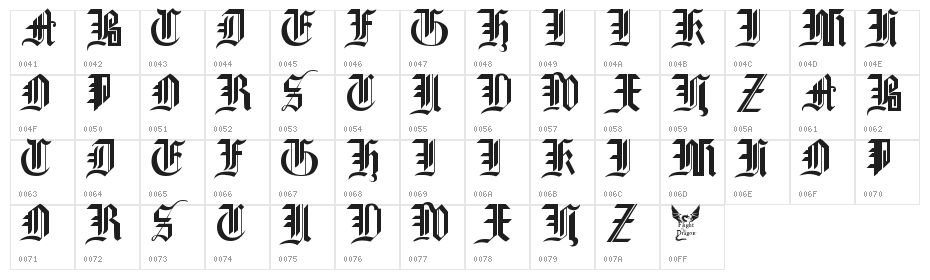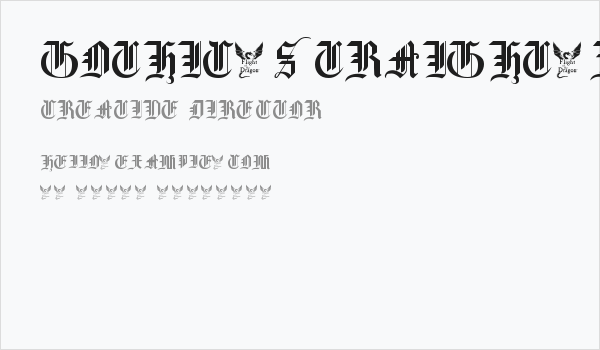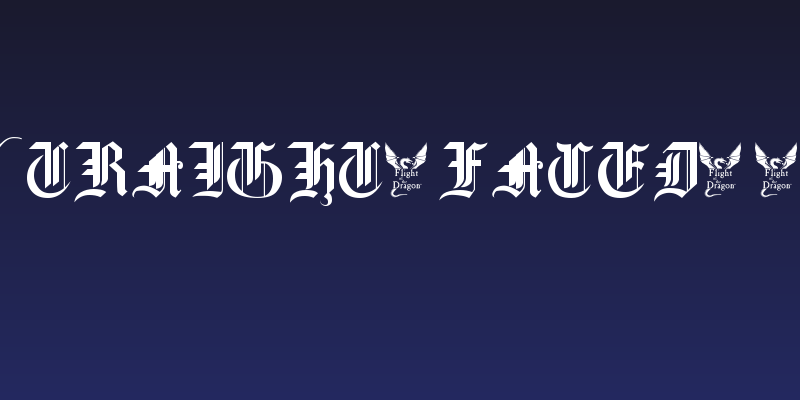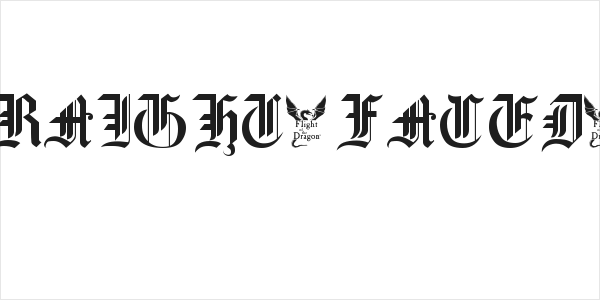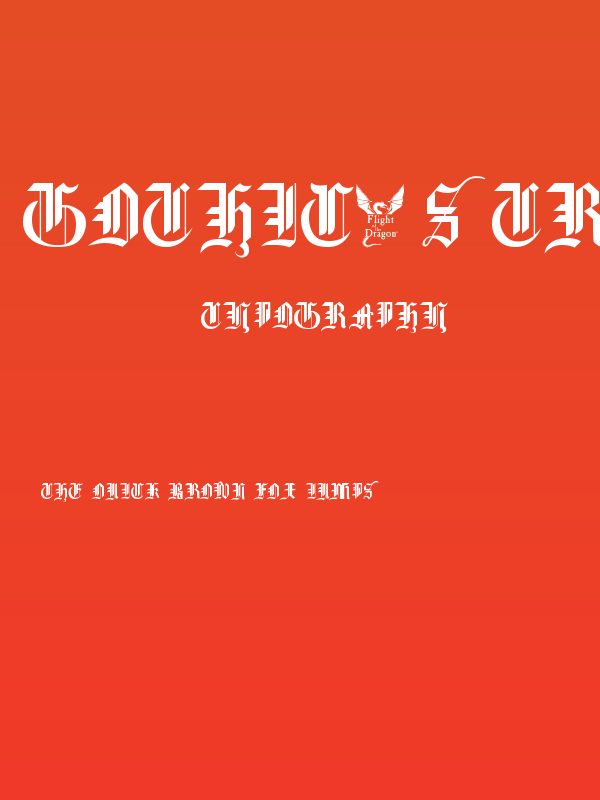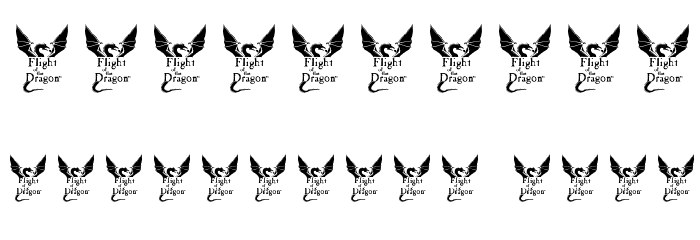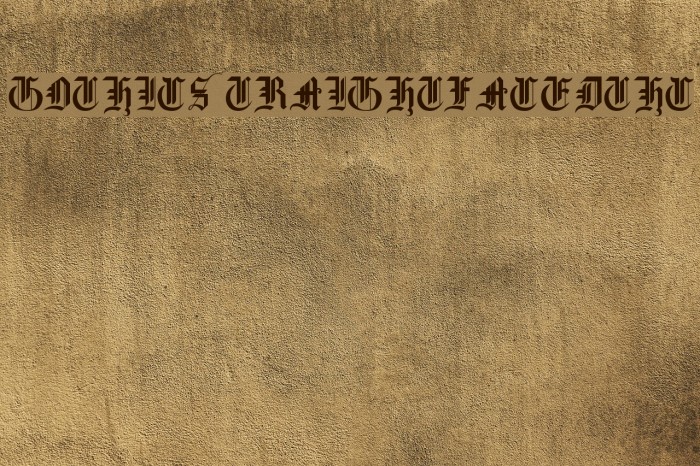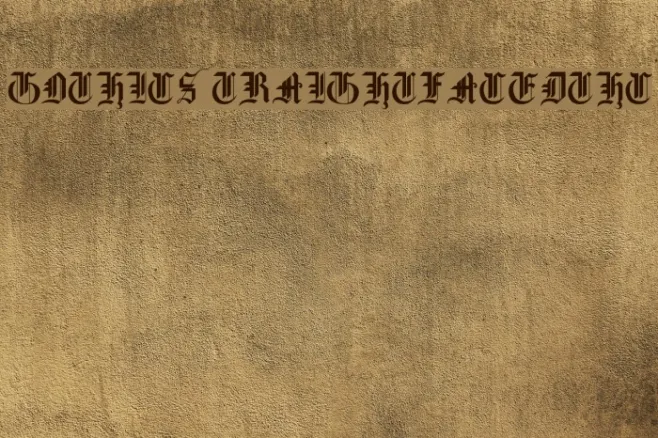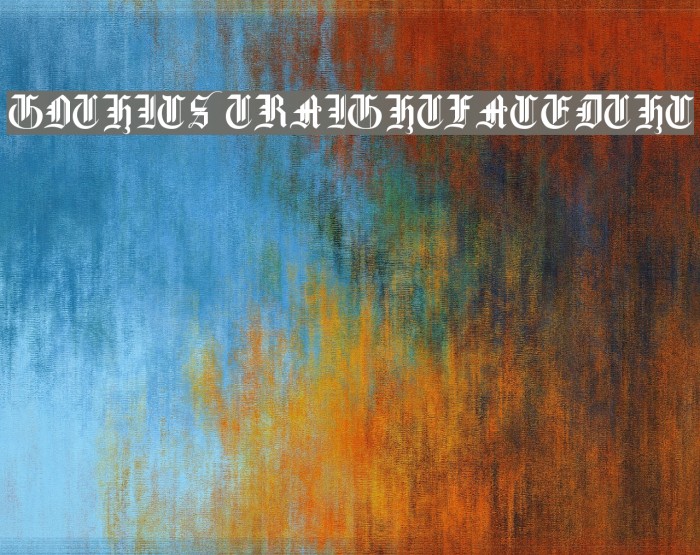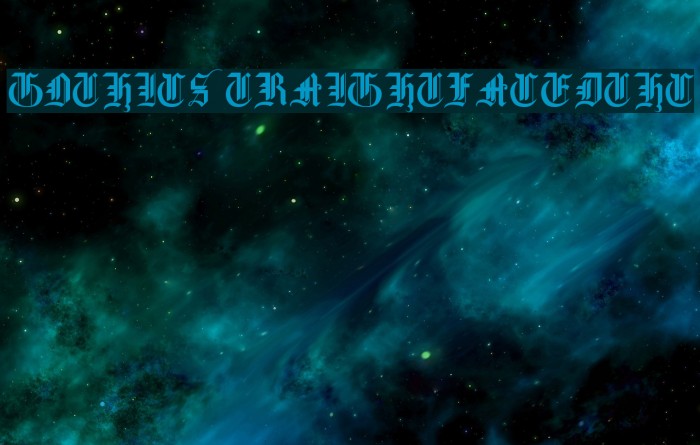
Gothic-Straight-Faced--16th-c- Font
✎ Gothic
| Progetti proposti | Ideal for historical documents, book covers, posters, and branding that requires a classic and sophisticated look. |